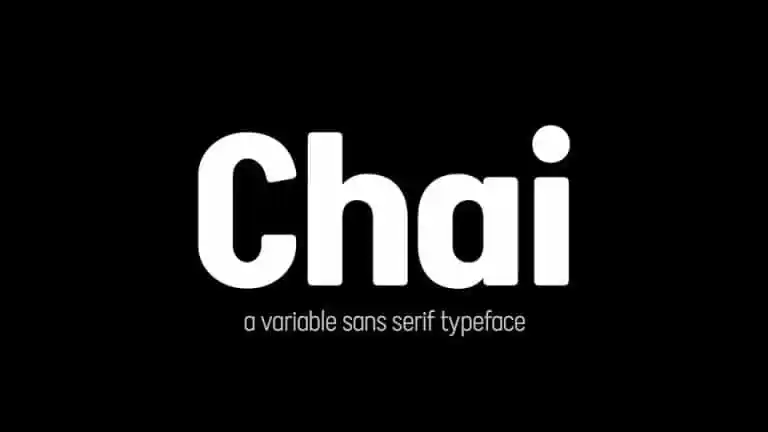
Chai Sans Serif Font – Download Grátis
A Chai Sans Serif é uma fonte sem serif extremamente versátil que funciona excepcionalmente bem tanto em grandes quanto em pequenos tamanhos. Ela foi criada e compartilhada pelo designer Tall Chai. Esta fonte é um família de tipo variável para exibição, ideal para títulos, declarações, headlines, anúncios, introduções, outrosos e textos de destaque. Embora as famílias de tipos para exibição tradicionalmente sejam mais formais e rígidas em sua abordagem, a Chai adiciona leves curvas suaves e um toque menos claro aos caracteres para adicionar uma informalidade humana ao seu design.